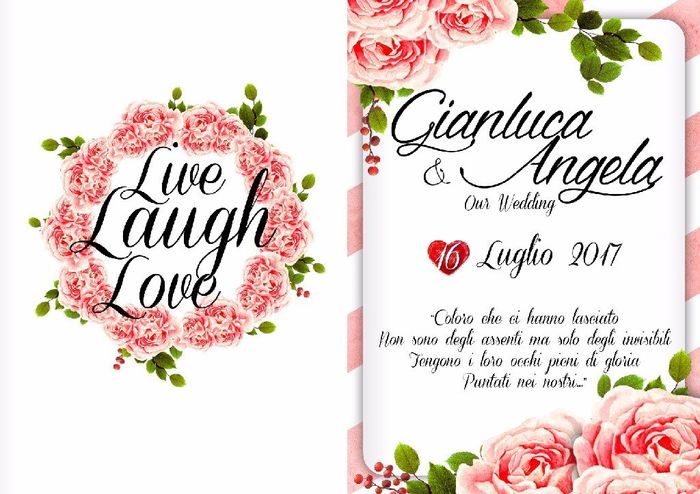
Font carini
Ciao belle, Sono in balia delle partecipazioni.le stiano facendo noi e sto cercando un font carino un po in corsivo ma chiaro ed elegante.avete idee?grazieeeee😘